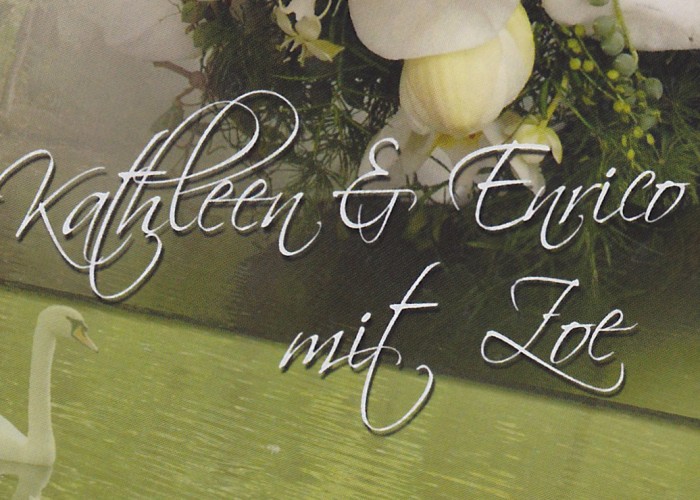
Welche geschwungene (?) "Schreib?schrift" ist das?
(Er)kennt jemand diese Schriftart und kennt deren genaue Bezeichnung?
Mir liegt ein DM-Fotobuch vor, welches 2011 erstellt wurde, doch kann ich diese Schrift in meiner Software nicht mehr finden.